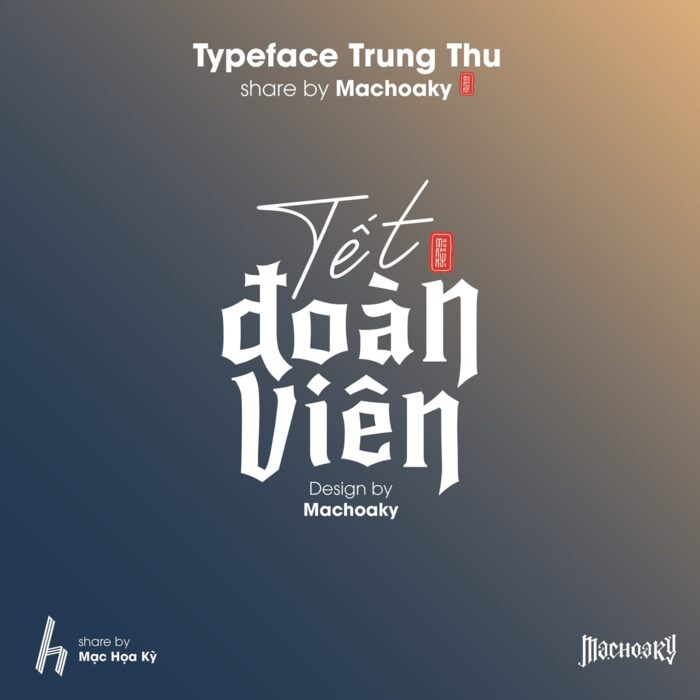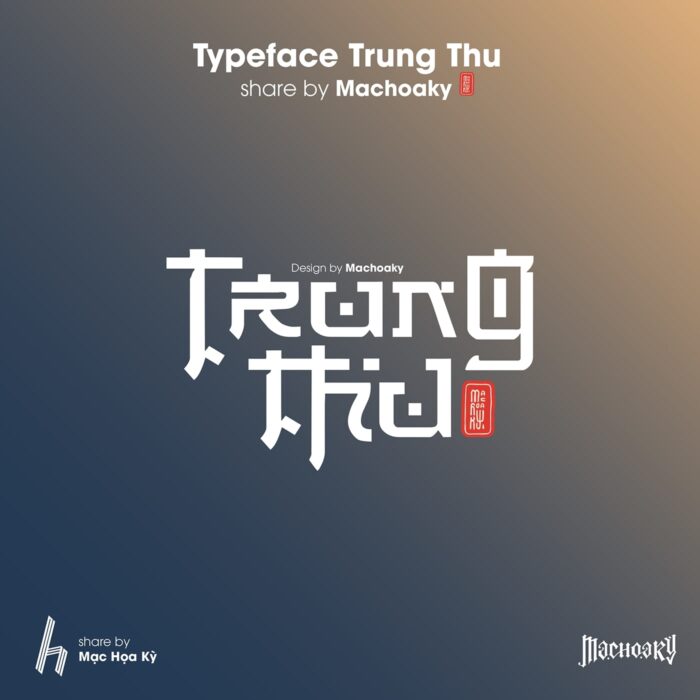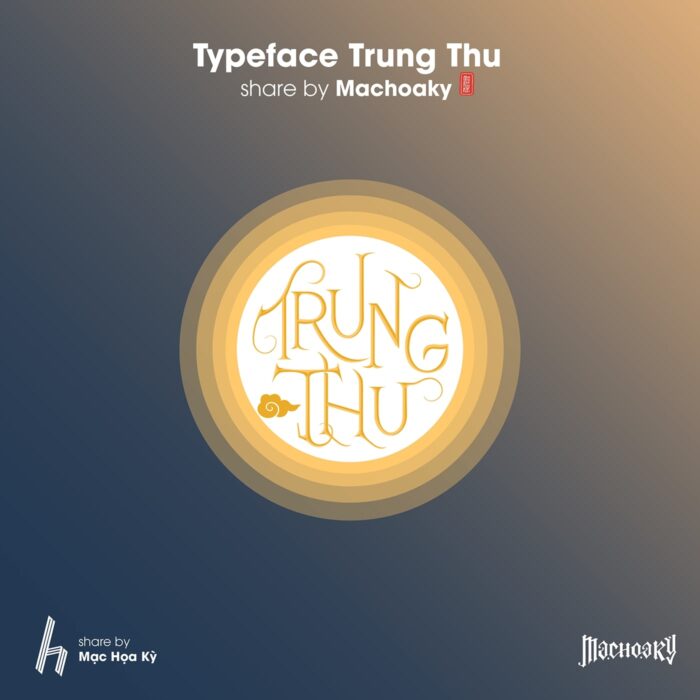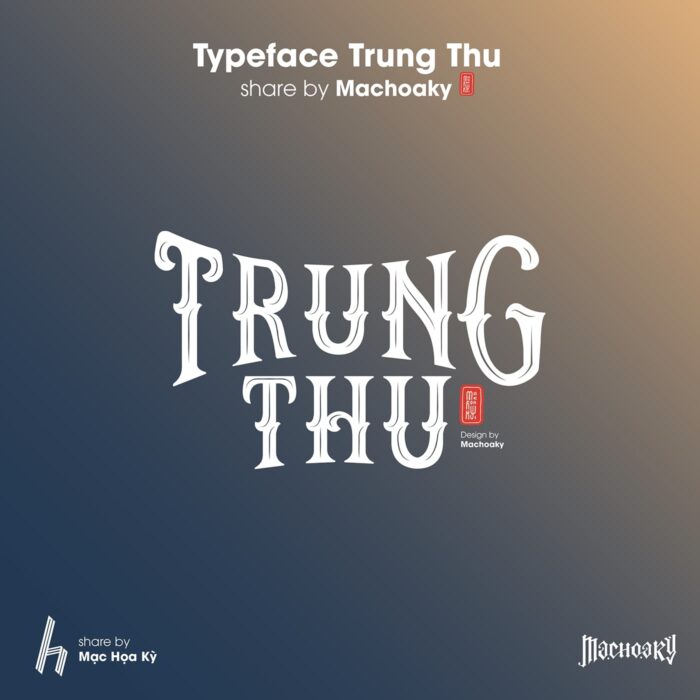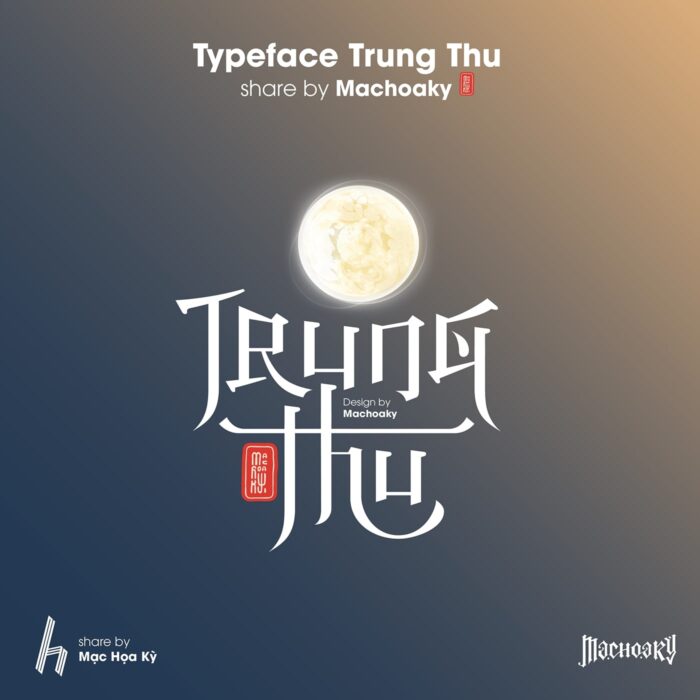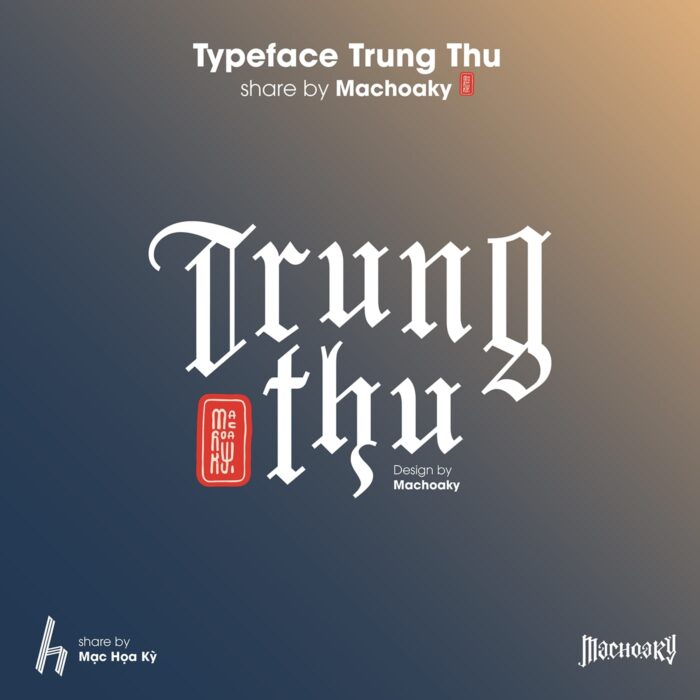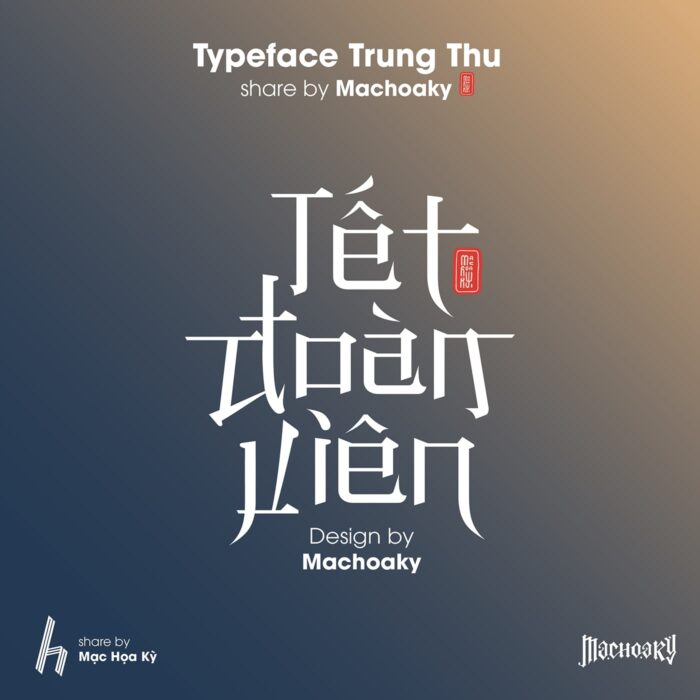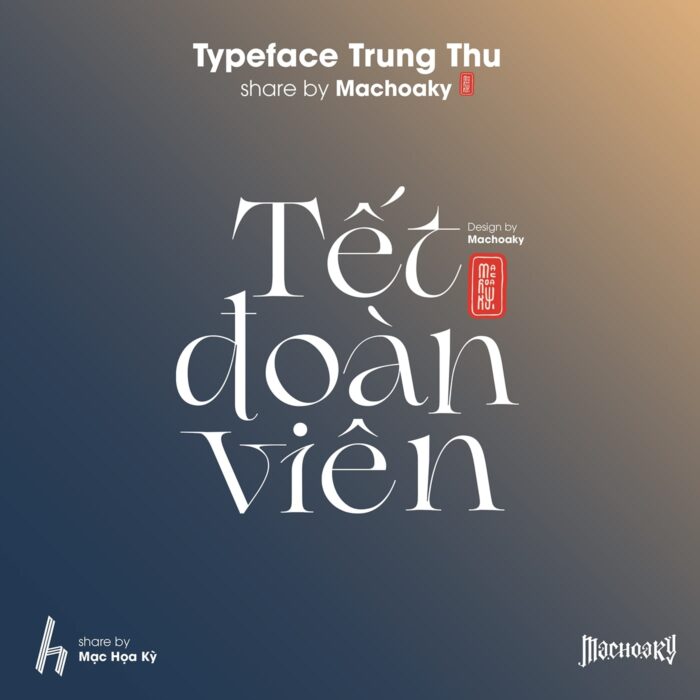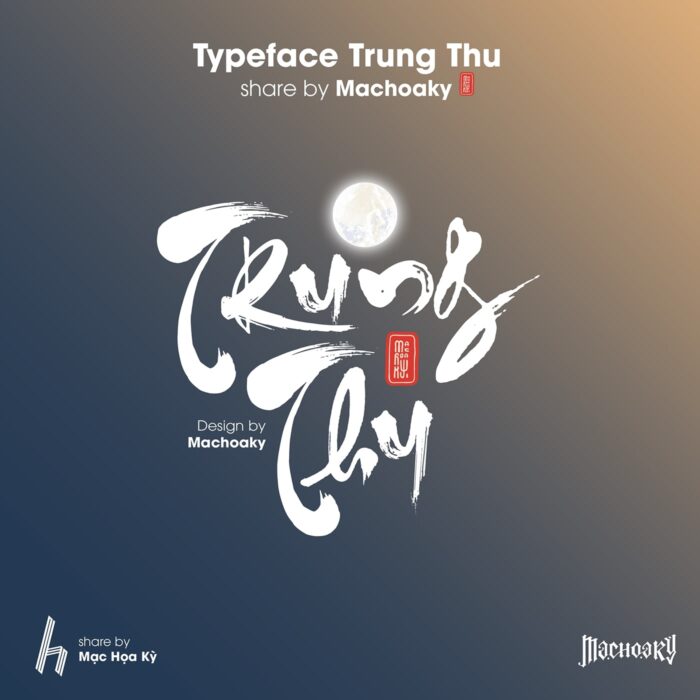
Bộ Typeface Trung Thu miễn phí tuyệt đẹp
Bộ typography với chủ đề Trung Thu này được thiết kế bởi Mạc Hoa Kỳ (Machoaky). Lấy cảm hứng từ những đặc trưng văn hóa và hình ảnh biểu tượng của Tết Trung Thu, mỗi kiểu chữ trong bộ sưu tập này đều mang đậm nét truyền thống và nghệ thuật, kết hợp giữa phong cách cổ điển và hiện đại. Bộ typography thể hiện các từ như “Trung Thu”, “Tết Đoàn Viên” qua nhiều phong cách khác nhau, từ những nét chữ cứng cáp, sắc nét cho đến mềm mại, uyển chuyển, gợi lên không khí ấm áp và đoàn tụ của ngày lễ.
Điểm đặc biệt là các thiết kế không chỉ truyền tải được tinh thần của Tết Trung Thu mà còn rất linh hoạt, có thể ứng dụng trong nhiều sản phẩm sáng tạo như thiệp chúc mừng, poster, banner, và các ấn phẩm quảng cáo. Với sự sáng tạo và tinh tế trong từng chi tiết, bộ typography này là sự lựa chọn lý tưởng để tôn vinh văn hóa Trung Thu trong các thiết kế hiện đại.